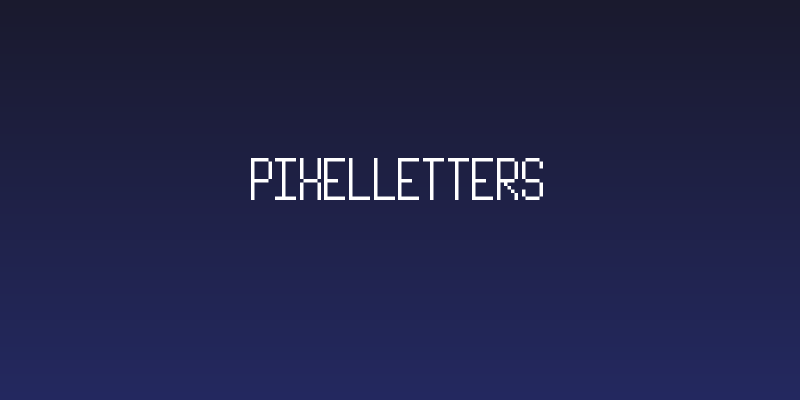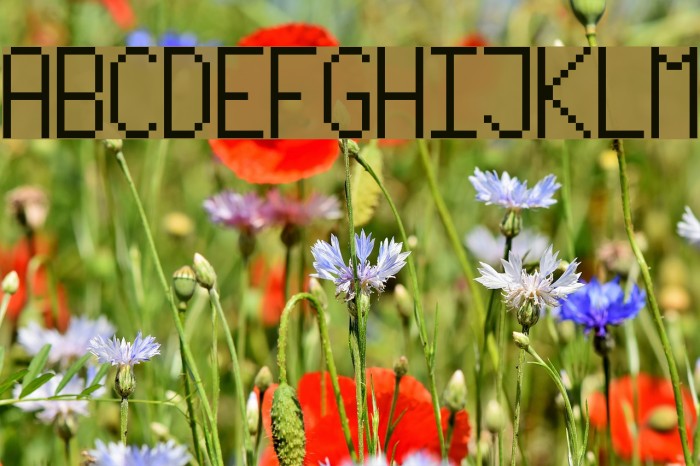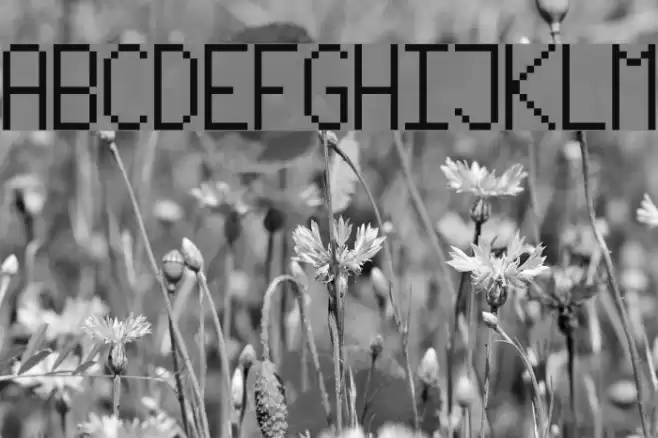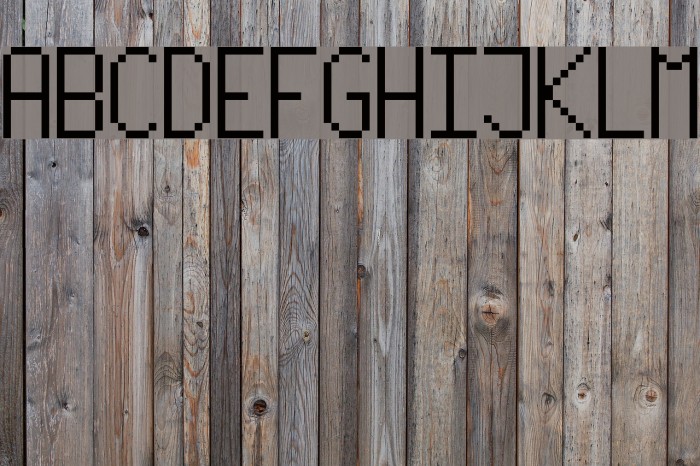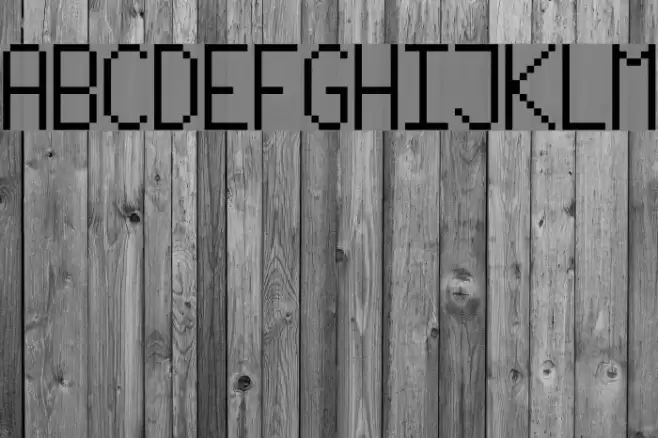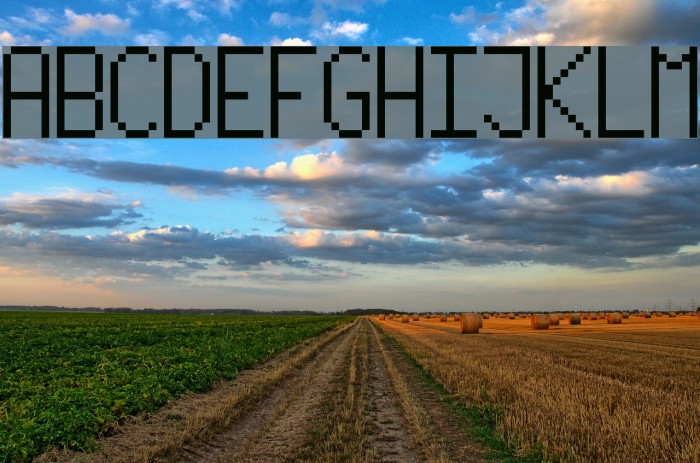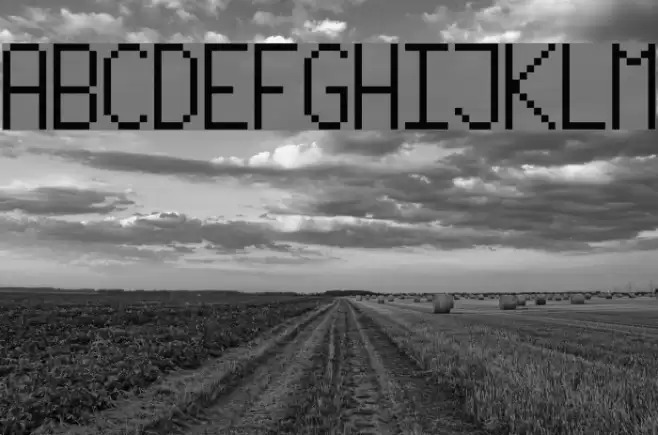
PixelLetters Font
| おすすめプロジェクト | Ideal for video game graphics, retro-themed posters, digital art projects, and any design requiring a nostalgic digital feel. |